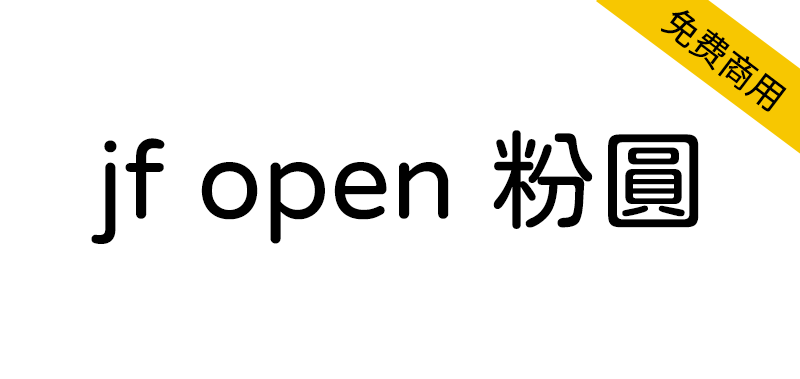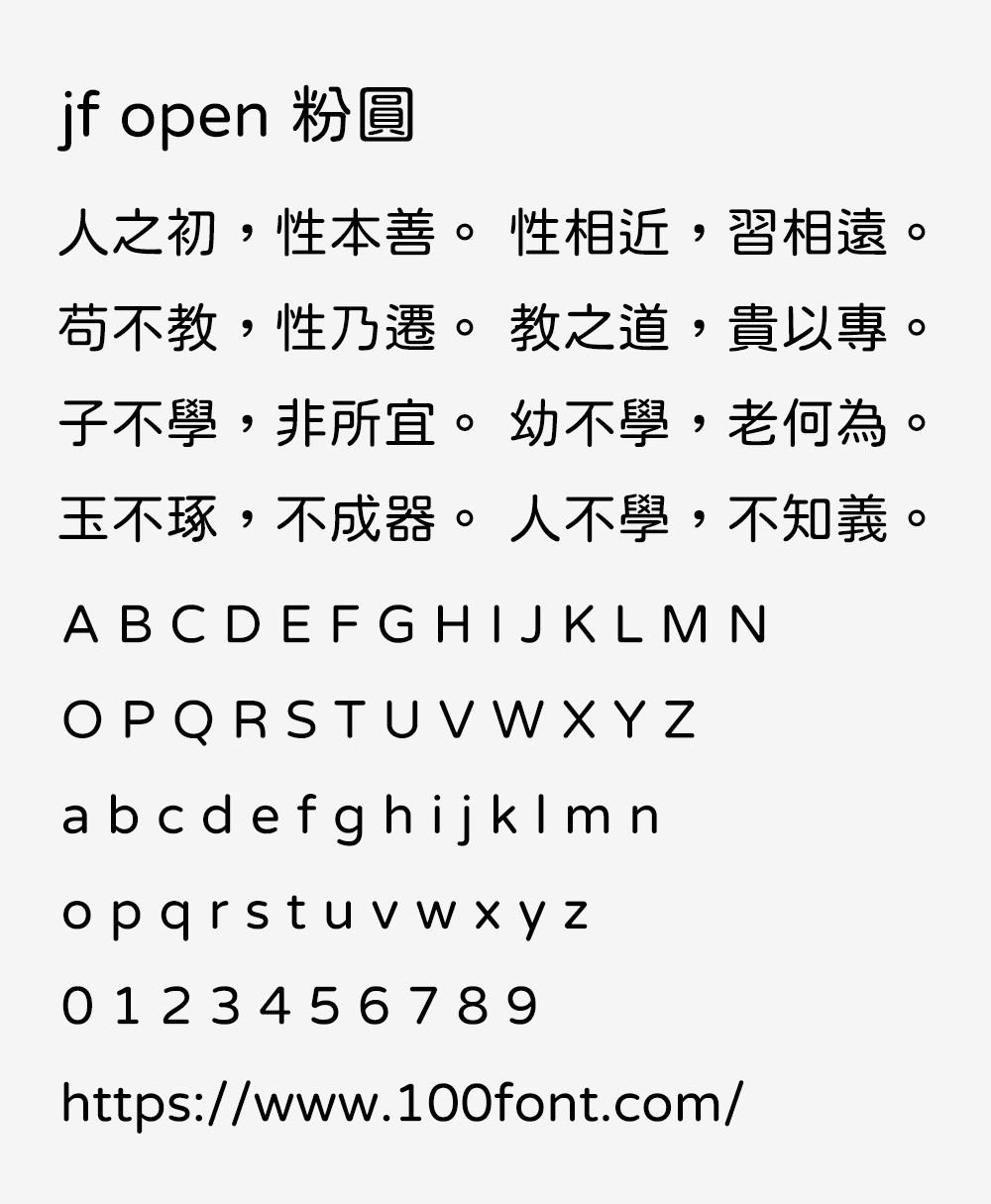
jf open粉圆是基于小杉圆体改作,由justfont设计师针对台湾日常应用加以优化的开源字型,以OFL开源授权发布,欢迎大家自由应用、自由优化、自由改作!
为了满足台湾的使用和排版需求,我们在原来的小杉圆体基础上增加了近2700个常用的台湾字符、注音符号,甚至台湾闽南语拼音和汉字。除了字符,我们的设计师还修改了排版设置,提高了字体的质量,使其更加美观。总之,jf open粉圆包括以下更改:
●笔划重新设计:对原始字符的不均匀笔划粗细进行调整和校正。
●排版调整:将小杉圆体中的日文标点符号更改为台湾使用的繁体中文标点符号。。
●新增字符:新增近2700个常用台湾字符和台湾闽南语字符,以及新设计的注音符号和台湾拼音符号。